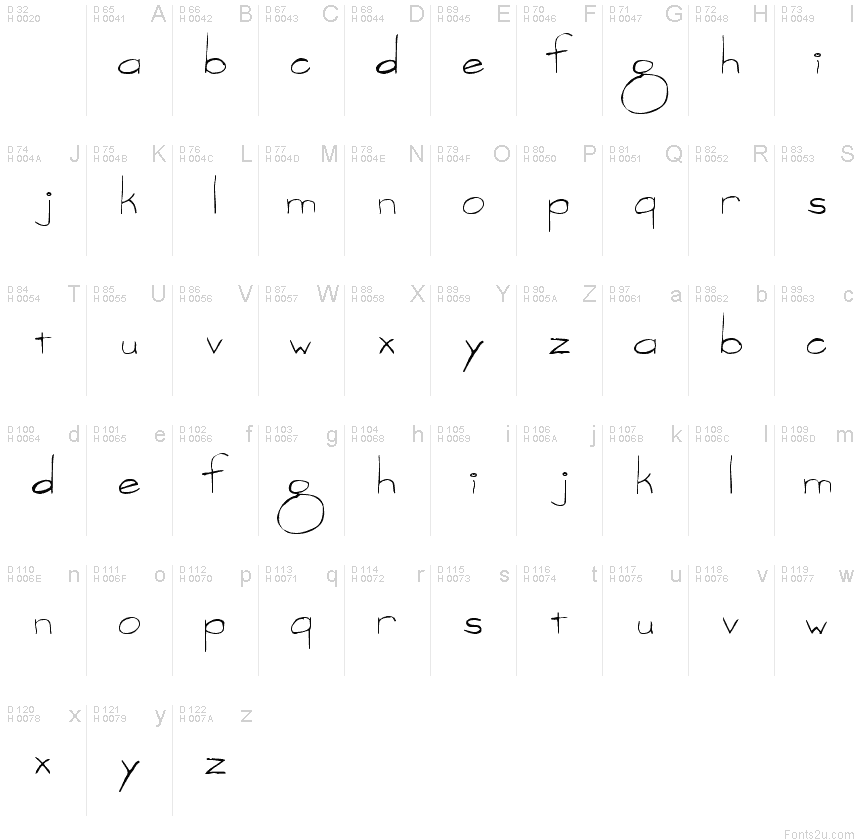
Vargas je bezplatné ručně psané písmo s uvolněným a osobitým charakterem připomínajícím rychlé tahy fixou. Písmena stojí na širokých zaoblených smyčkách a dlouhých, lehce rozechvělých tazích, přičemž hravé, nadměrné spodní dotahy dodávají celému písmu lehký a neformální rytmus.
Skvěle se hodí na plakáty, obaly butikových produktů, branding kaváren, neformální knižní obálky i titulky na sociální sítě, kde potřebujete, aby písmo působilo jako kreslené, nikoliv strojené. Použijte ho pro krátké nadpisy, jména nebo iniciály, když chcete, aby vynikl ten velký, smyčkovitý pohyb a kompozice zůstala vzdušná.